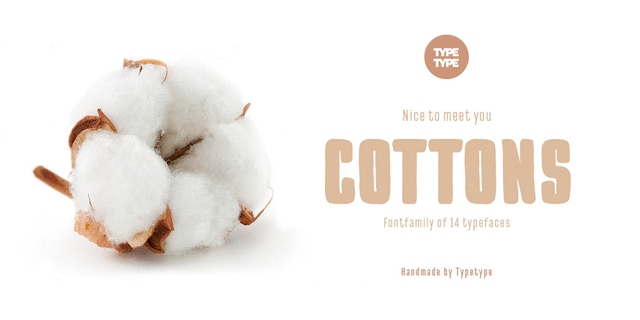
TT Cottons идеальный помощник дизайнера. Шрифт наполнен вдохновением и уютом, которые добавляют легкости и домашней атмосферы любой поверхности (любой среде). Это семейство шрифтов напоминает о свежем воздухе весны и о ручной работе. Каждое начертание создано реальным инструментом. Например, черное начертание нарисовано реальной кистью, а тонкое – рапидографом. Благодаря 7 вариантам насыщенности вы можете легко выбрать идеальный вариант Cottons для своего макета. Узкие пропорции позволяют поместить большой текст в небольшом пространстве. Шрифт Разработан Иваном Гладких в студии TypeType в 2016 году.
натуральный, экономный, современный, высокий, модный, статичный, аккуратный, зеленый, экологичный, стройный, худой, спокойный, деликатный, чистый, легкий, тонкий, интимный, лаконичный, воздушный, прозрачный, хрупкий, невесомый, качественный, прямоугольный, городской, мирный, домашний, уютный, ручной, свежий, рукотворный, приятный, комфортный, весенний, проволочный, органический, дружелюбный, простой, доверительный, стабильный, крафтовый, симпатичный, живой, ламповый, надежный, устойчивый, бытовой, теплый, мягкий, хлопковый, важный, заметный, громкий, убедительный, уверенный, летний, вкусный, тесный, тяжелый, плотный, семейный
гигиена, косметика, чистота, диета, АСМР, графика, иллюстрация, здоровье, парфюмерия, отдых, завтрак, интерьер, весна, хюгге, инстаграм, дом, торговля, кафе, хенд мейд, утро, текстиль, одежда, магазин, полотенце, пижама, вата, еда, шоу, телевидение, булочная, сок, подушка, постельное белье, одеяло, мебель, игрушка, спальня Стилистика: